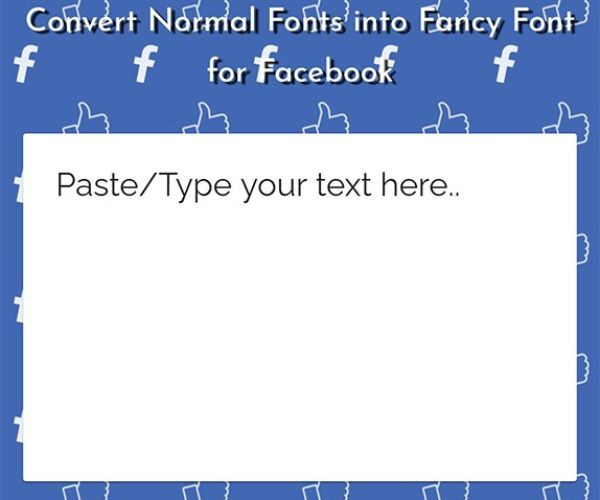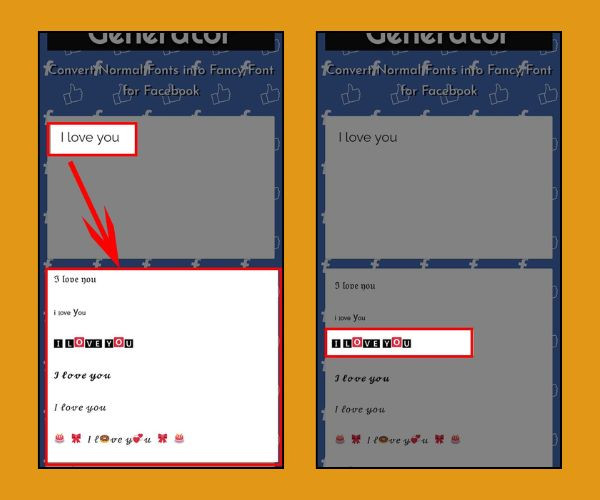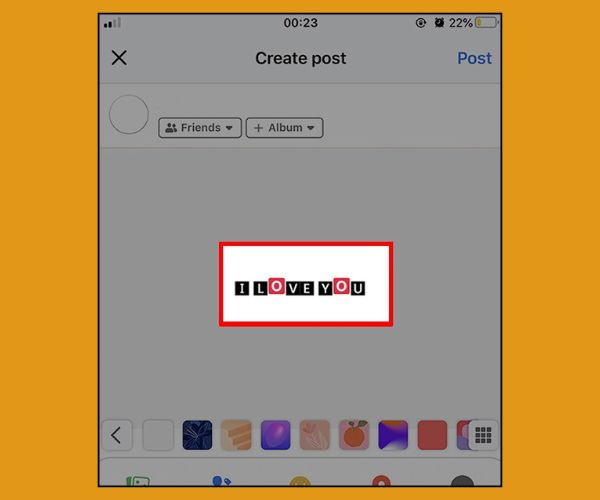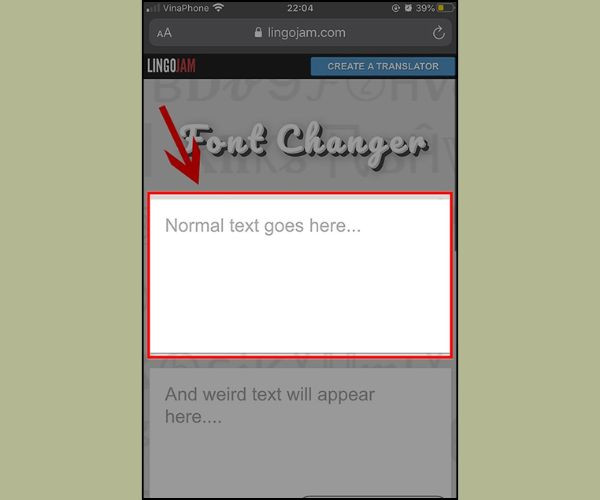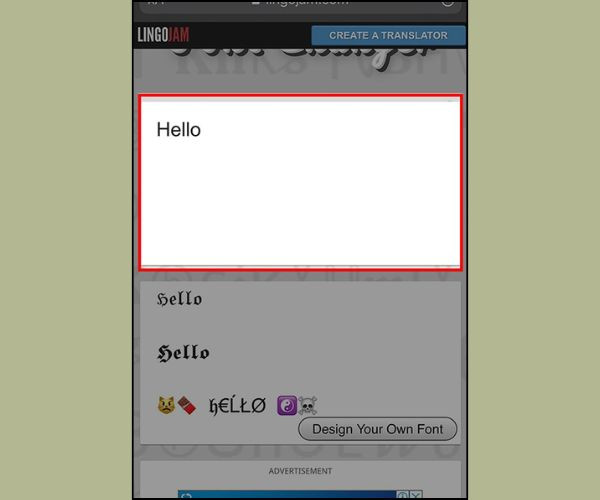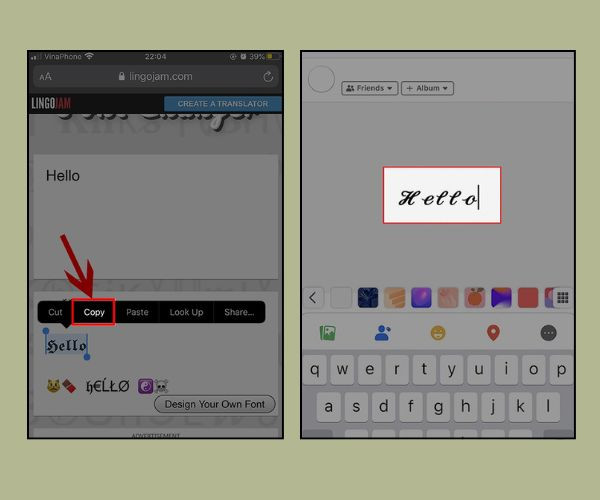
Font Generator là gì? Top 5 công cụ tạo font chữ độc đáo
Font Generator giúp người dùng chuyển đổi font chữ mặc định của mạng xã hội, blog, diễn đàn,..trở nên lạ mắt, thu hút và ấn tượng hơn. Cùng khám phá nhé!
Font chữ đặc biệt giống như một “tấm áo đẹp” giúp nội dung của bạn thú vị hơn. Các trang web Font Generator sẽ cung cấp kho font chữ độc đáo giúp bạn thỏa sức sáng tạo cho status, bio, tin nhắn,.... Dưới bài viết này, FASTCARE sẽ mách bạn top 5 trang Font Generator miễn phí và cách chuyển đổi font chữ siêu nhanh, siêu dễ.
Font Generator
Font Generator là gì?
Font Generator là trình tạo font chữ độc đáo giúp bạn sáng tạo nội dung theo cách riêng. Hiện nay có rất nhiều trang web Font Generator giúp bạn lựa chọn font chữ để biến tấu cho status, bio đăng trên Facebook, Instagram, Twitter,...
Các trang mạng xã hội này chỉ có font chữ mặc định, vì thế nếu muốn nội dung trở nên thu hút, mới mẻ hơn thì bạn hãy thử dùng Font Generator. Ngoài hiệu ứng font chữ mới lạ thì một số trang Font Generator còn có biểu tượng cảm xúc ngộ nghĩnh, giúp trang cá nhân của bạn nổi bật hơn.
Một số công cụ tạo font chữ độc đáo siêu dễ
Dưới đây là một số trình Font Generator cung cấp font chữ sáng tạo lạ mắt. FASTCARE sẽ mách bạn cách sử dụng của từng công cụ để “thổi hồn” cho nội dung đăng tải trên mạng xã hội của bạn trở nên độc đáo hơn bao giờ hết.
Facebook Font Generator
Giới thiệu: Công cụ này được phát triển bởi Font Villa, là một trong những trình chuyển đổi font chữ thông dụng nhất hiện nay. Sở hữu hơn 20 font chữ độc đáo và các ký tự đặc biệt, biểu tượng lạ mắt, đây là công cụ hữu ích để chỉnh sửa status, bio, tin nhắn, comment,...
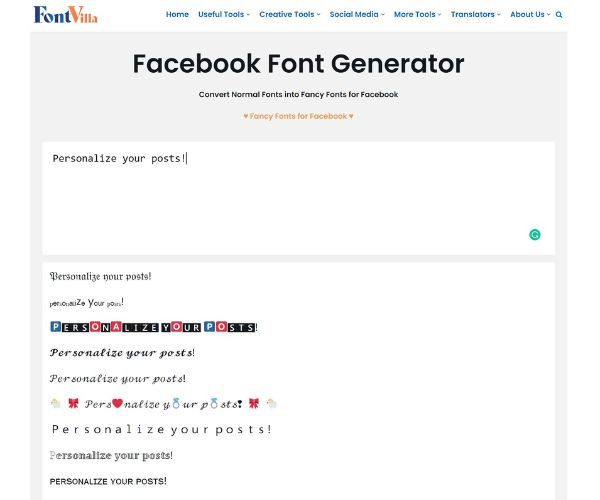
Facebook Font Generator bước 1
• Bước 2: Nhập nội dung cần chuyển đổi font chữ vào ô “Paste/Type your text here…”
Facebook Font Generator bước 2
• Bước 3: Lựa chọn font chữ yêu thích của bạn > Nhấn giữ nội dung và chọn Copy.
Facebook Font Generator bước 3
• Bước 4: Dán nội dung vừa lưu lên trang bạn muốn đăng tải, ví dụ đăng status lên Facebook.
Facebook Font Generator bước 4
Symbols & Emoticons
Giới thiệu: Đây là một trong những trình Font Generator phổ biến nhất, với hơn 20 kiểu chữ lạ mắt. Symbols & Emoticons giúp bạn chuyển đổi font chữ mặc định của status, tin nhắn, bio, bình luận,...trở nên mới mẻ, ấn tượng hơn rất nhiều.
Symbols & Emoticons bước 1
• Bước 2: Nhập nội dung cần đổi font chữ vào khung “Your text here…”.
Symbols & Emoticons bước 2
• Bước 3: Nhấn vào nút Convert > Lựa chọn font chữ mà bạn yêu thích.
Symbols & Emoticons bước 3
• Bước 4: Copy nội dung đã được chuyển đổi sang font chữ mới > Dán vào trang mà bạn muốn đăng tải.
Symbols & Emoticons bước 4
Font Changer
Giới thiệu: Đây là công cụ chuyển đổi font chữ của Lingojam, sở hữu hơn 50 kiểu font độc đáo. Bạn có thể thay đổi font chữ dễ dàng với Font Changer cho các nội dung đăng tải trên mạng xã hội, blog, diễn đàn,...
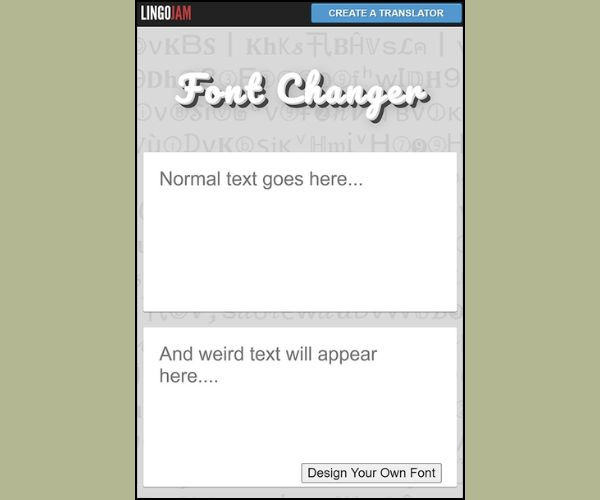
Font Changer bước 1
• Bước 2: Nhập nội dung status, tin nhắn,...mà bạn muốn đổi font chữ vào ô “Normal text goes here…”.
Font Changer bước 2
• Bước 3: Lướt xem nội dung đã được chuyển sang các font chữ mới lạ và chọn font mà bạn yêu thích.
Font Changer bước 3
• Bước 4: Copy nội dung và dán vào trang mà bạn muốn đăng.
Font Changer bước 4
YayText
Giới thiệu: Đây là một trong những kho text fonts độc đáo nhất mà bạn không thể bỏ lỡ. Với hơn 25 kiểu font mới lạ, từ in đậm, in nghiêng cho đến chữ gạch chân, chữ đứng,...đều có đầy đủ. Font chữ đẹp mắt giúp bạn làm mới nội dung trên tin nhắn, status,...
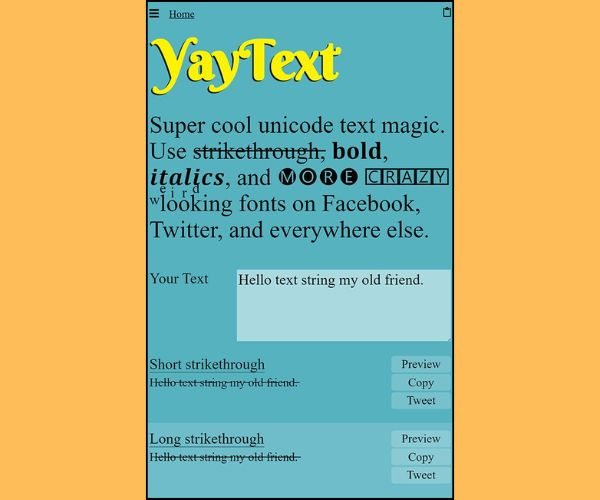
• Bước 1: Truy cập vào trang website YayText.
YayText bước 1
• Bước 2: Tại ô “Your Text”, bạn nhập văn bản cần chuyển đổi font chữ.
YayText bước 2
• Bước 3: YayText giúp bạn chuyển đổi nội dung sang nhiều font chữ khác nhau. Bạn lướt xem và lựa chọn font chữ yêu thích nhất.
• Bước 4: Copy nội dung và dán vào trang mà bạn muốn đăng.
YayText bước 4
AhaChat
Giới thiệu: Facebook Text Generator của Ahachat cho phép bạn lựa chọn và chuyển đổi font chữ linh hoạt. Tất cả các font đều là font Unicode, có thể hiển thị trên mạng xã hội, blog, bình luận trên báo,...giúp bạn đổi mới giao diện nội dung khi đăng tải.
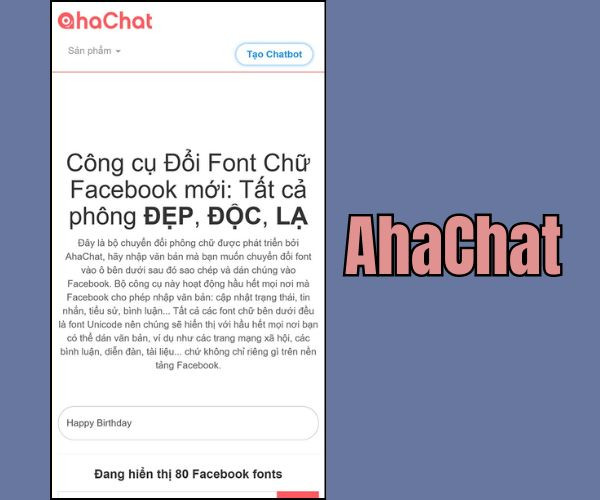
• Bước 1: Truy cập vào trang website AhaChat.
AhaChat bước 1
• Bước 2: Bạn nhập nội dung status, tin nhắn, bio,...cần đổi font chữ vào ô “Nhập text vào đây”.